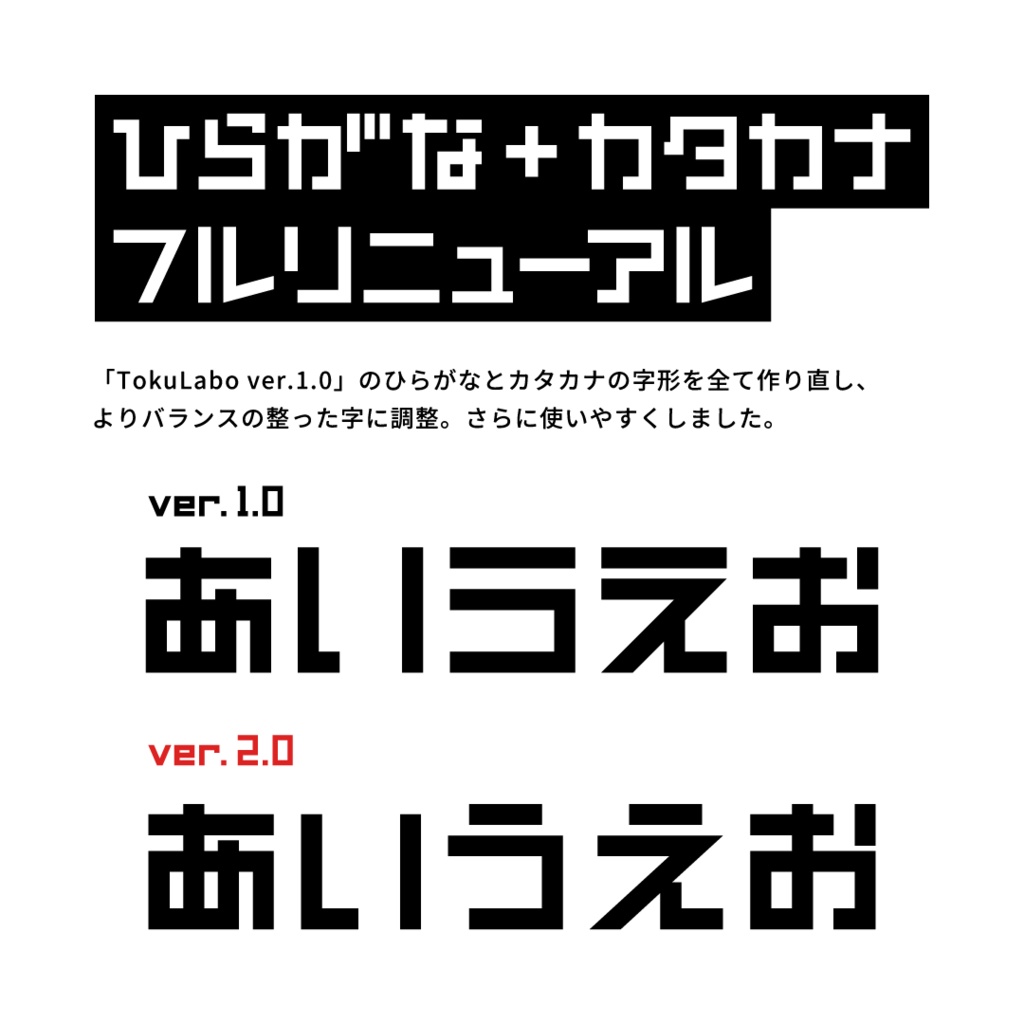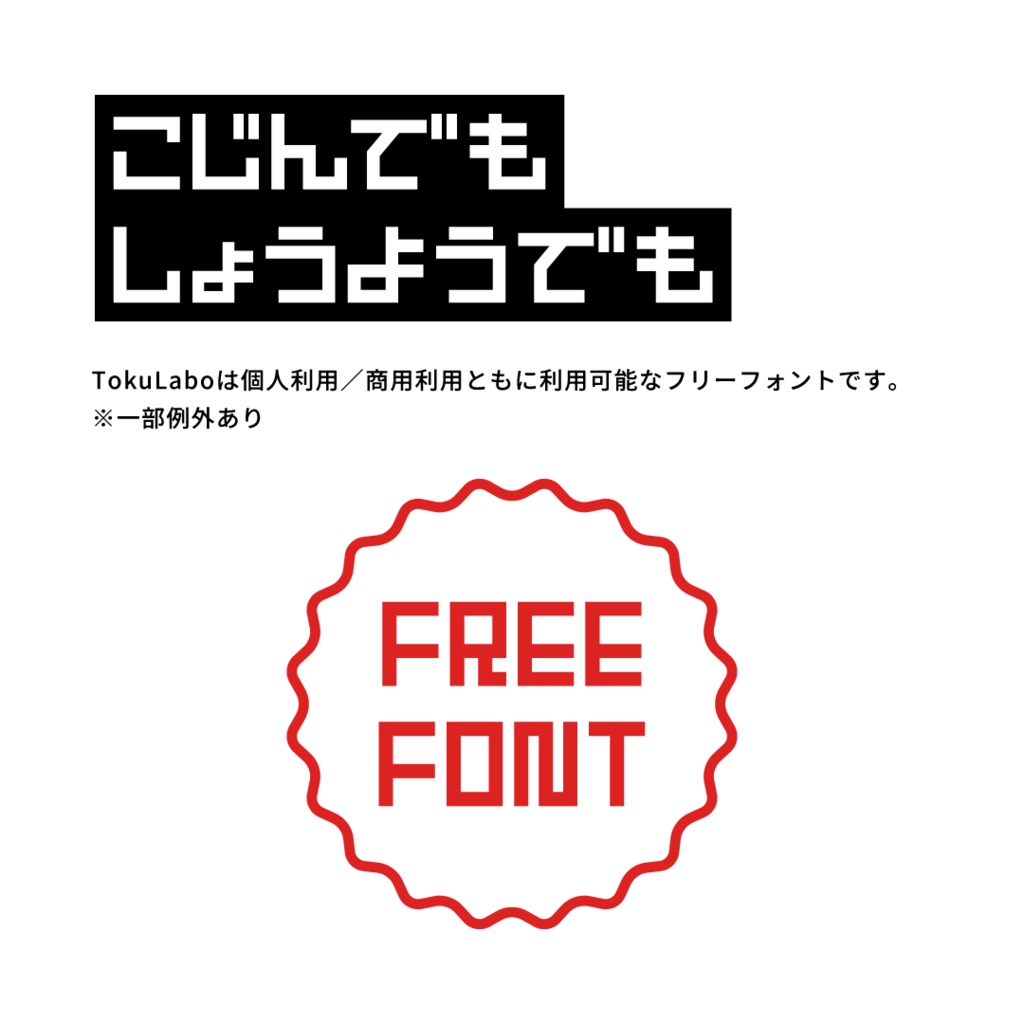
TokuLabo V2【フリーフォント】
◆TokuLaboとは?
作者がニコ生コミュニティ(なくなりました)で使っていたデザインを基に、趣味で作った、個人利用/商用利用可能 ※一部例外あり なOpenTypeフォントです。 趣味の副産物のため、作りの荒い箇所がございます。おてやわらかに…
◆収録文字